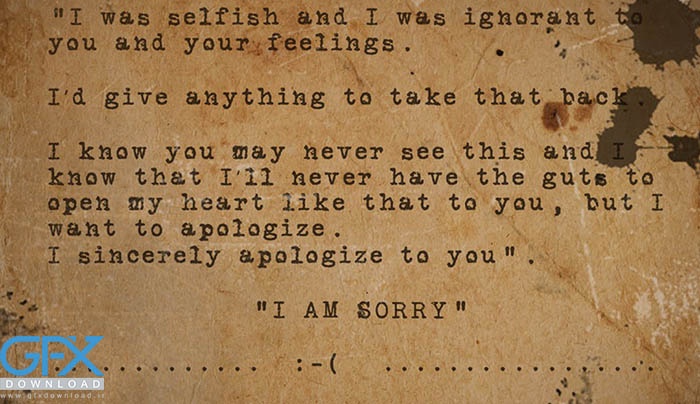
فونت انگلیسی ماشین تحریر Silk Remington یک فونت جدید ماشین تحریر است که برای القای حس واقعی ماشین تحریر قدیمی طراحی شده است. دارای هفت سبک ، Thin، Regular، Rough Regular ،SemiBold 5.Rough-SemiBold 6.Bold ، Rough Bold می باشد.